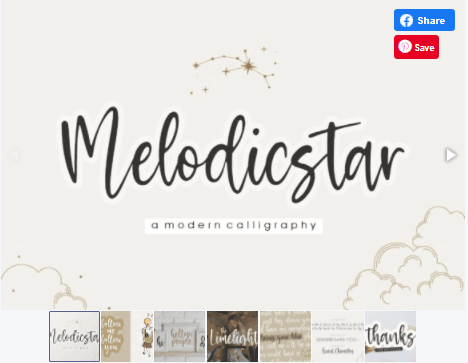
Melodicstar Font
Melodicstar – это прекрасный шрифт с очаровательными игривыми персонажами, которые, кажется, танцуют вдоль основной линии. Добавьте этот шрифт к своим самым творческим идеям и обратите внимание, как он их выделяет!